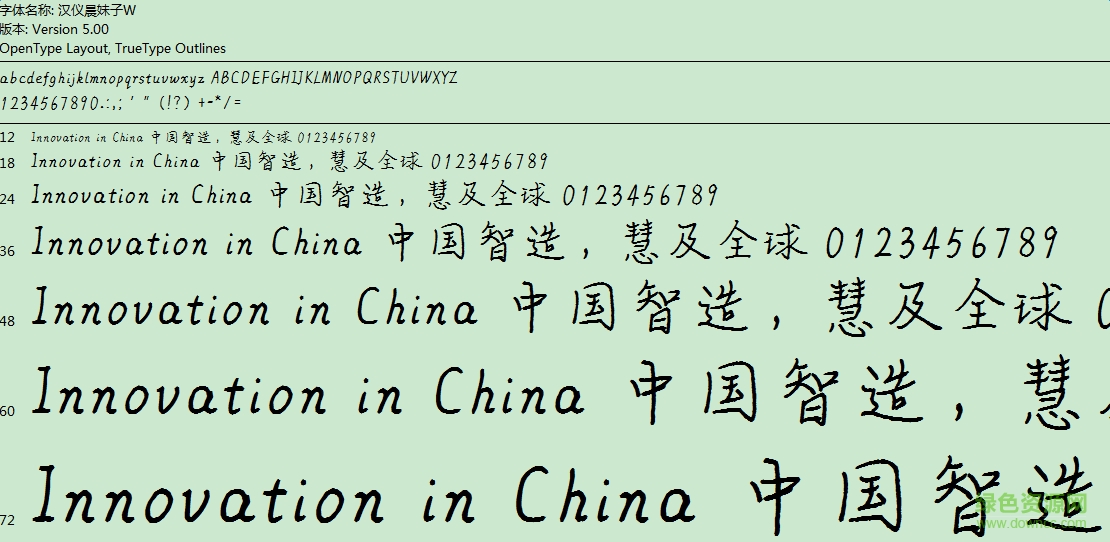
漢儀晨妹子w是漢儀系列手寫類字體軟件,整體效果隨心所欲,妹子氣息十足,在文章標(biāo)題設(shè)計(jì)方面有著不錯(cuò)的應(yīng)用,歡迎大家來綠色資源網(wǎng)踴躍下載哦!
漢儀晨妹子w是一款手寫字體,字體看起來簡(jiǎn)單明亮,隨手寫成,充滿青春活潑的味道,如同沐浴在陽光中。